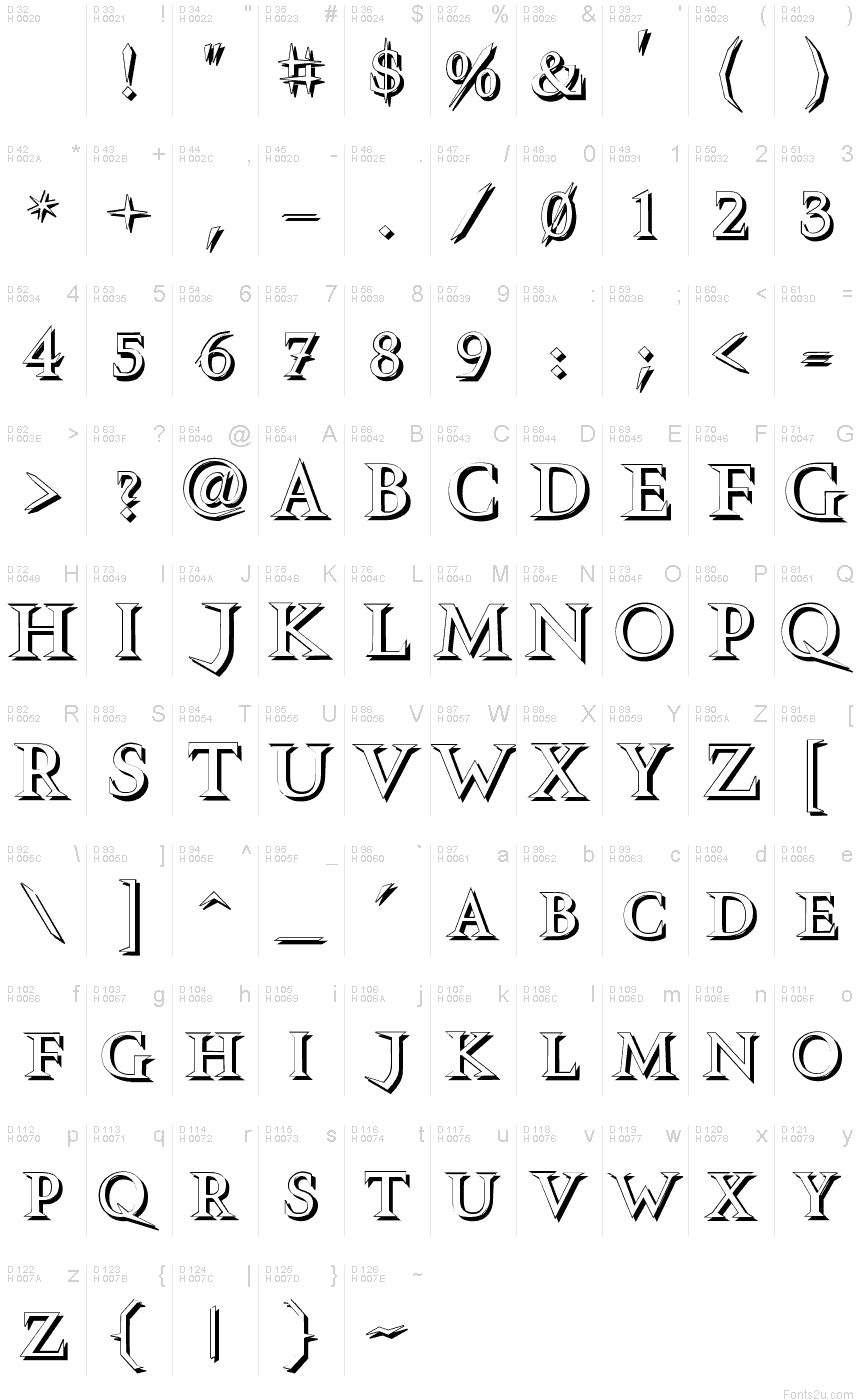
Podgląd czcionki VTCSwitchbladeRomanceShadowed
VTC Switchblade Romance Shadowed od V.T.C. Vigilante Typeface Corporation to darmowy krój pisma typu display, zawierający cieniowane wersaliki w stylu rzymskim, nawiązujący do dramatycznego klimatu starych plakatów. Litery łączą klasyczne formy inskrypcyjne z ostrzami przypominającymi krawędzie noży oraz wyraźnym cieniem, dzięki czemu całość sprawia wrażenie czegoś pomiędzy grawerowanym pomnikiem a tytułem pulpowego romansu.
Dzięki temu ten darmowy font jest naturalnym wyborem na okładki książek, ulotki zespołów, nagłówki plakatów, plansze tytułowe i monogramy, w których litery mają mieć charakter, a nie subtelność. Najlepiej sprawdza się w krótkich tekstach, ponieważ ostre wcięcia i dzielony cień nadają nawet prostym inicjałom czy nagłówkom napiętego, teatralnego wyrazu.